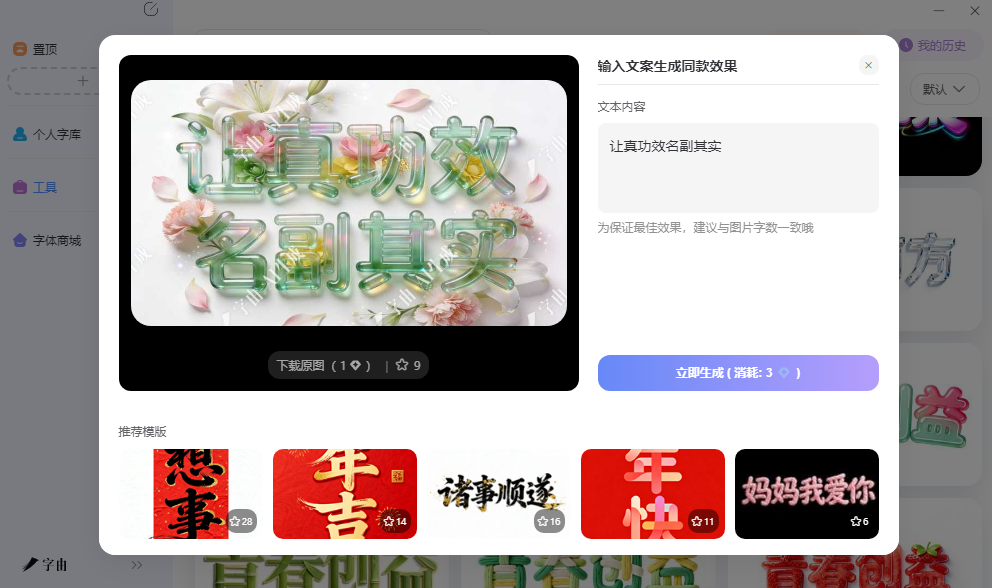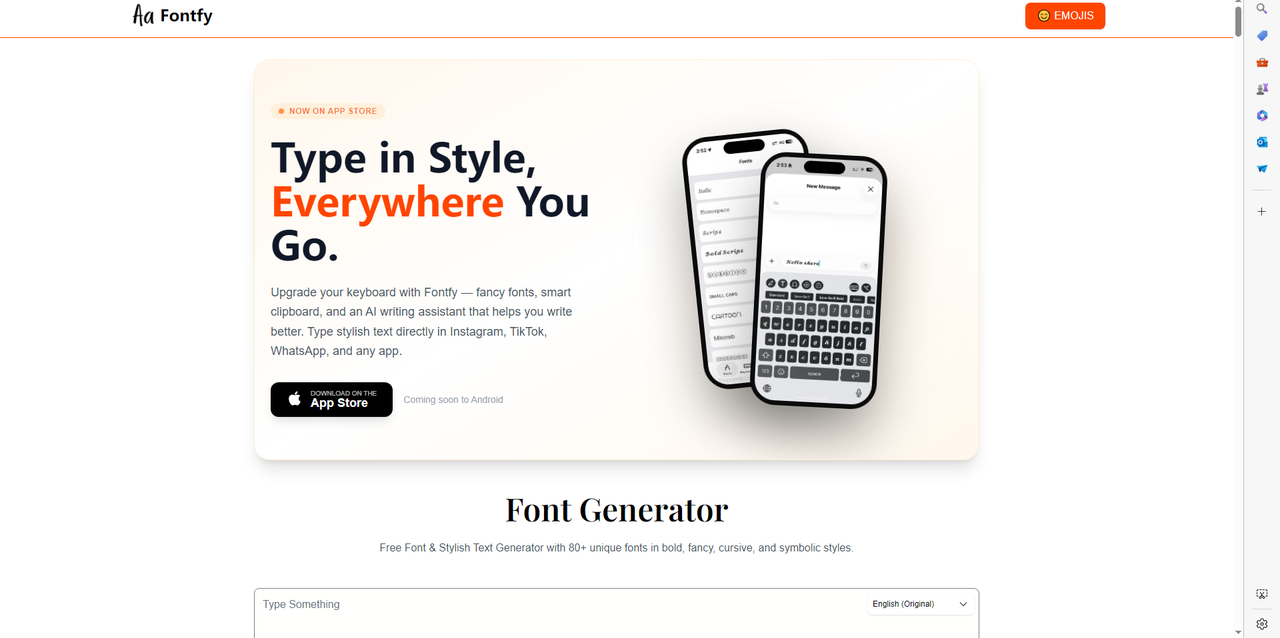
免费变形字体在线生成,玩转个性艺术字
把文字拉长、压扁、加扭曲效果,或者改成哥特体、花体字,这些操作在专业设计软件里需要调整多个参数。对于没有设计基础的用户,在线变形字体生成器提供了更简单的方案:输入文字,选择一个预置的变形样式,几秒钟就能看到结果。这些工具生成的结果大多支持一键复制粘贴,可以直接用在社交平台的昵称、简介、评论区,或者下载图片用于海报、封面。本文实测了5款变形字体生成工具,覆盖了从简单字符变形到完整艺术字图片生成的不同需求。
字由AI字体功能内置400多套文字特效模板,这个功能能满足你对变形字体的大部分要求,而且模板分类多种多样。每个模板的字体样式、文字特效、排版布局和背景颜色都是预先设置好的完整方案。
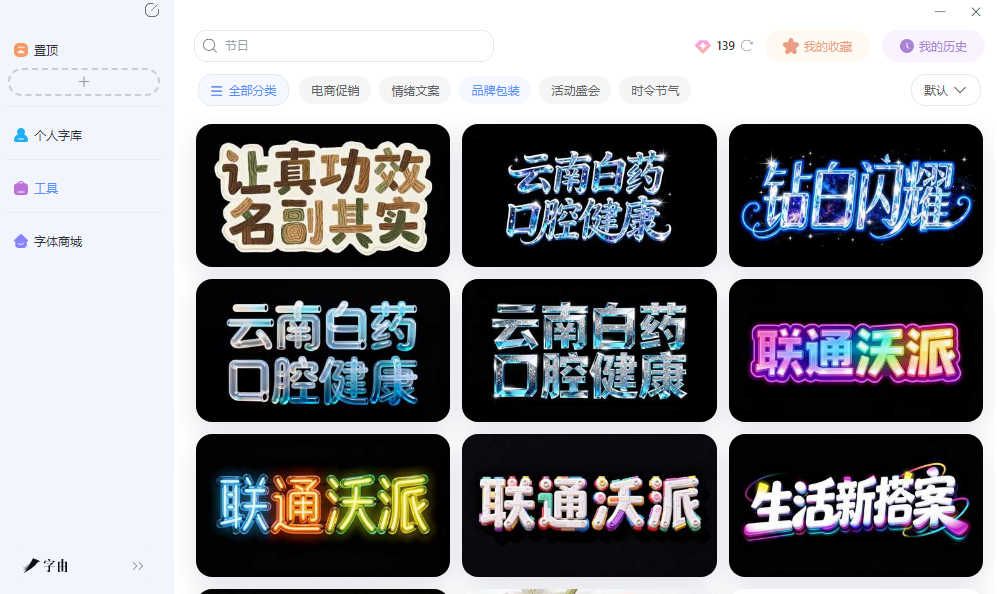
具体使用流程如下:打开字由客户端,进入AI字体模块,在左侧标签栏选择需要的风格类别,系统展示该类别下的所有模板预览。用户输入自己的文案,选择其中一个模板,点击生成按钮,等待10到15秒,系统输出一张透明背景的PNG图片。
图片默认分辨率为2K级别,支持缩放使用。生成一张图片消耗3个算力点,字由平台每日登录赠送6个算力点。该功能主要服务于需要快速产出版本标题文字的场景,例如电商活动主图、短视频封面文字、活动海报主标题、社交媒体宣传配图等。
用户不需要具备设计软件操作知识,也不需要手动调整字体、发光、阴影、描边等参数。如果对生成结果不满意,用户可以更换模板重新生成,或调整文案长度使其接近模板示例的字符数以保持排版效果。
2、Fontfy、
第二个工具是Fontfy。它是一个移动端优先的字体转换工具,提供iOS App下载,Android版本即将上线。Fontfy提供了80多种独特字体样式,包括粗体、花体、草书、符号体等。用户可以在App内直接输入文字,选择需要的字体样式,然后复制转换后的文本,粘贴到Instagram、TikTok、WhatsApp等社交平台的输入框中。Fontfy还内置了智能剪贴板和AI写作助手,可以帮助用户润色文案。
Fontfy的优势在于它直接嵌入手机键盘,用户打字时就可以选择花体字样式,不需要在浏览器和社交App之间来回切换。适用于经常在手机上发布社交媒体内容、希望对文字进行个性化美化的用户。目前提供免费下载,部分高级功能可能需要付费。
3、Font Generator
第三个工具是一个专门生成特殊字体的在线生成器。页面提供多种变形变体,用户在上方输入框输入文字,下方会列出各种变体的预览效果。每个变体旁边有一个复制按钮,点击即可将转换后的文本复制到剪贴板。用户可以将这些文本粘贴到社交媒体、游戏昵称、论坛签名等任何支持文本输入的地方。这类诅咒字体通常带有尖锐的笔画、倾斜的角度或特殊的装饰符号,适合用于哥特风格、万圣节主题或需要暗黑气质的场景。这个工具不需要注册,完全免费,输出的是纯文本字符(基于Unicode映射),不生成图片。适合临时需要一种特殊风格文字的用户。
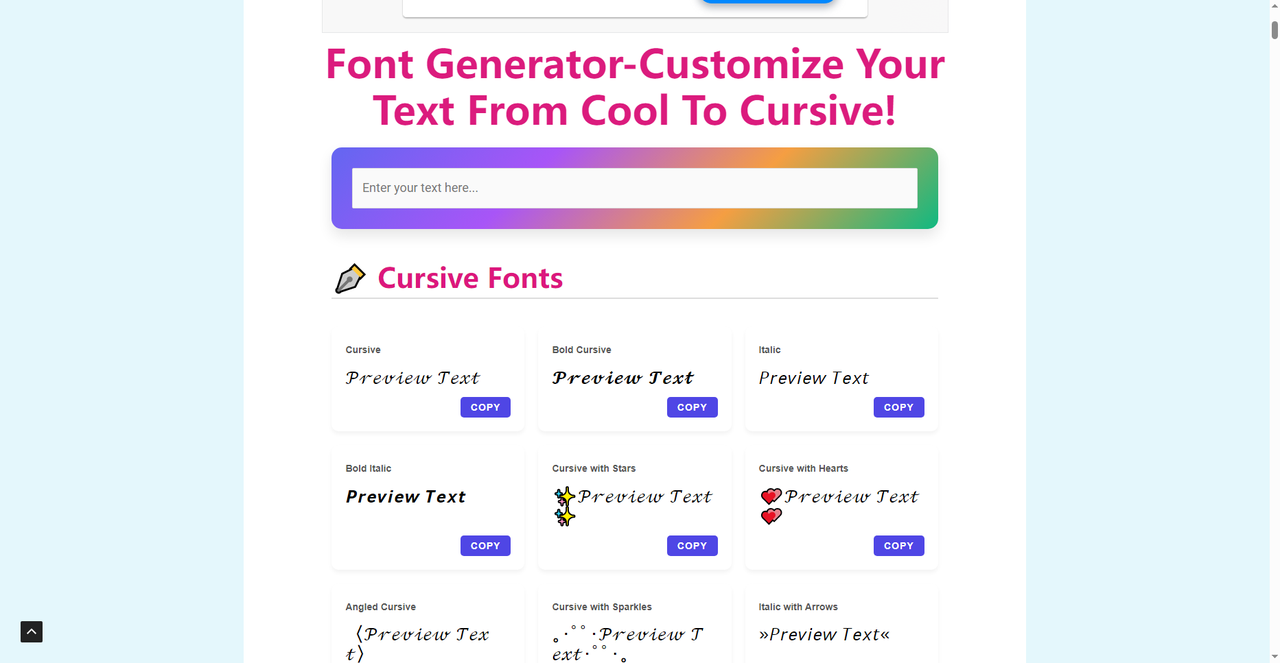
4、fontgen.app
第四个工具是fontgen.app。它的界面简洁,提供文字输入框和字号调节滑块(默认20px)。用户输入文字后,可以选择生成多种样式:Bold Font(粗体)、Italic Font(斜体)、Cursive Font(草书)、Bold Italic Font(粗斜体)、Sans Serif Italic Font(无衬线斜体)、Bold Cursive Font(粗草书)等。每个样式下方会显示转换后的文本预览,用户点击对应的结果即可复制。这个工具生成的是Unicode字符,不生成图片,因此可以跨平台复制粘贴,接收方不需要安装任何字体。它适用于需要将普通文字转换成粗体或斜体样式用于网页、社交媒体、代码注释等场景。字号调节功能仅影响预览显示大小,不影响复制后的文本字符本身。工具完全免费,无需注册。
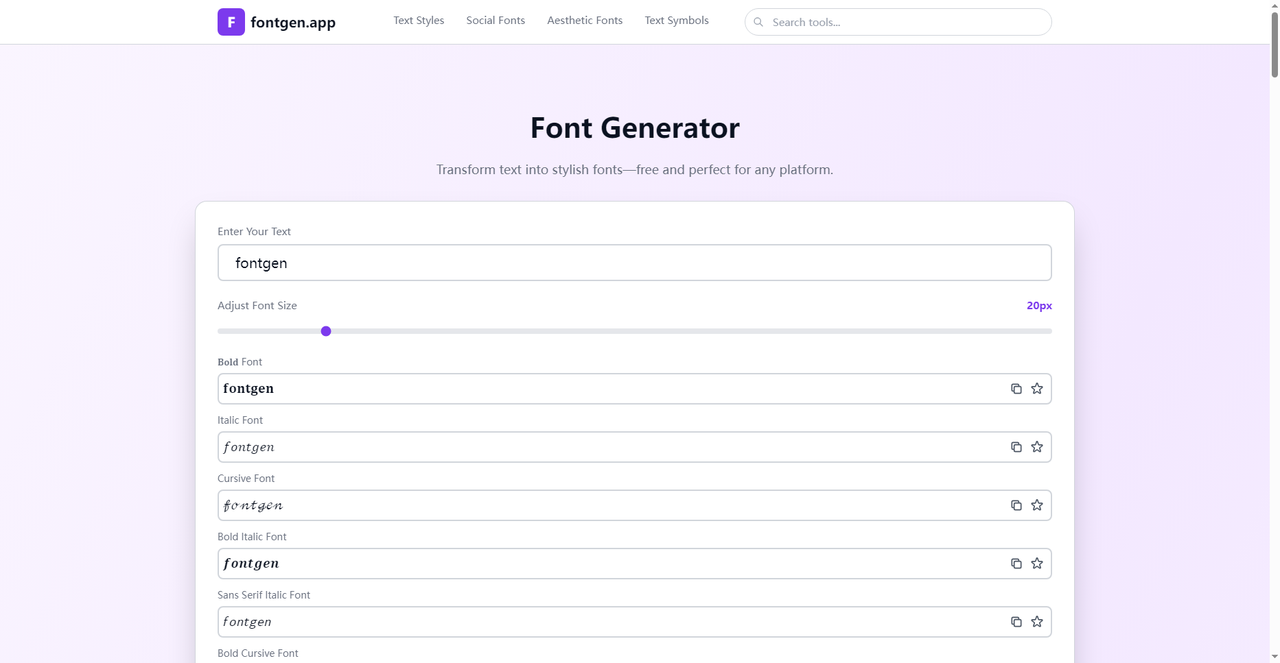
5、GoLogo
第五个网站是GoLogo。它专门用于字体变形Logo设计,用户输入品牌名称,选择行业分类,系统会生成多个字体变形Logo方案。页面下方展示了设计案例,例如绿茵花田、风暴酿、瑞愿福泽、烈火麦香等,每个案例都展示了不同的字体变形效果。
GoLogo提供的字体变形包括拉伸、倾斜、笔画连笔、装饰线条等效果,适合制作品牌标识。用户对生成结果不满意可以重新生成或调整品牌名称,也可以对方案进行细节修改。
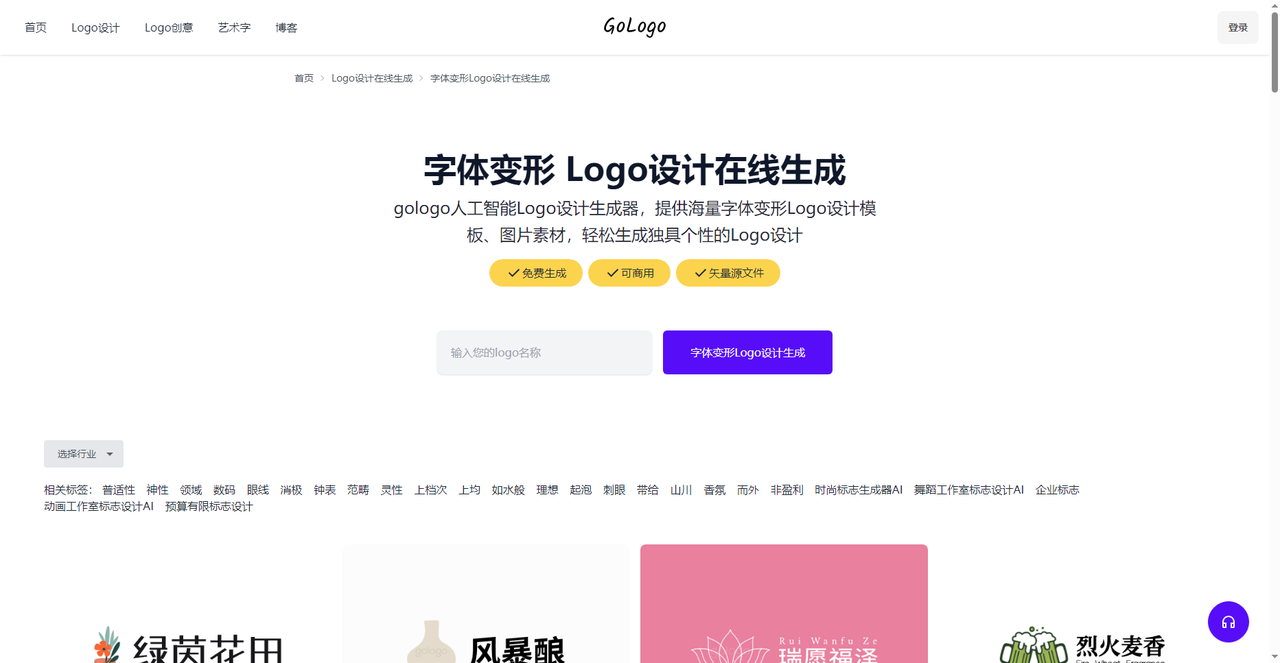
五个变形字体生成工具,适用场景不同。字由最适合需要高清艺术字图片的设计师,模板多,生成快,适合海报和封面;Fontfy主打移动端,80多种字体直接嵌入手机键盘,适合社交平台文字美化;Font Generator提供哥特风、斜体、带闪粉等变体,一键复制粘贴;fontgen.app可调节字号,生成粗体、斜体、草书等样式,输出纯文本;GoLogo专注于Logo设计,字体变形效果多样,支持矢量下载和商业使用。输入文字,选择对应工具,几秒钟就能得到变形后的文字效果。不需要学习专业软件,在线即可完成。